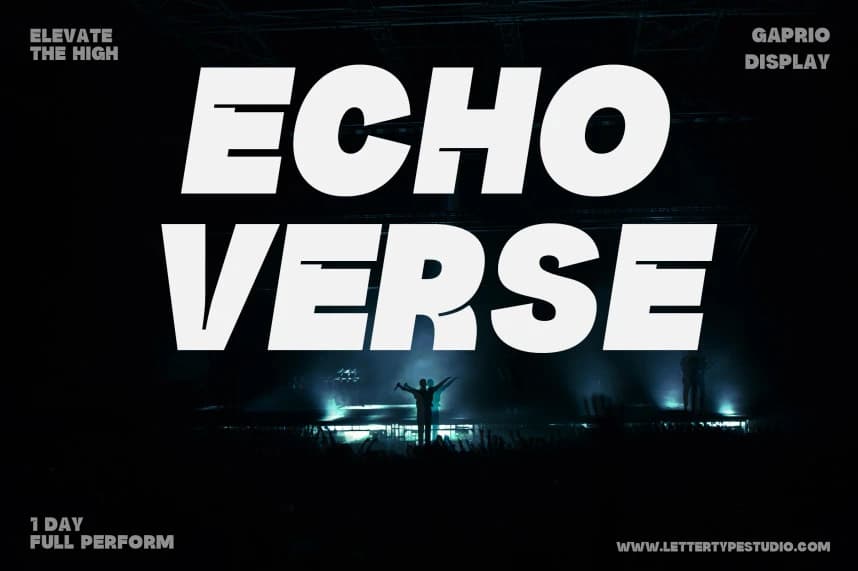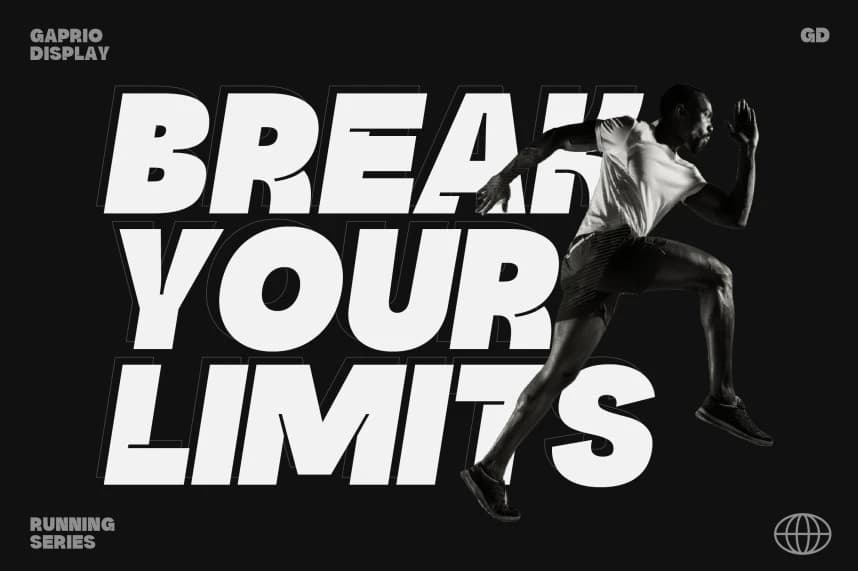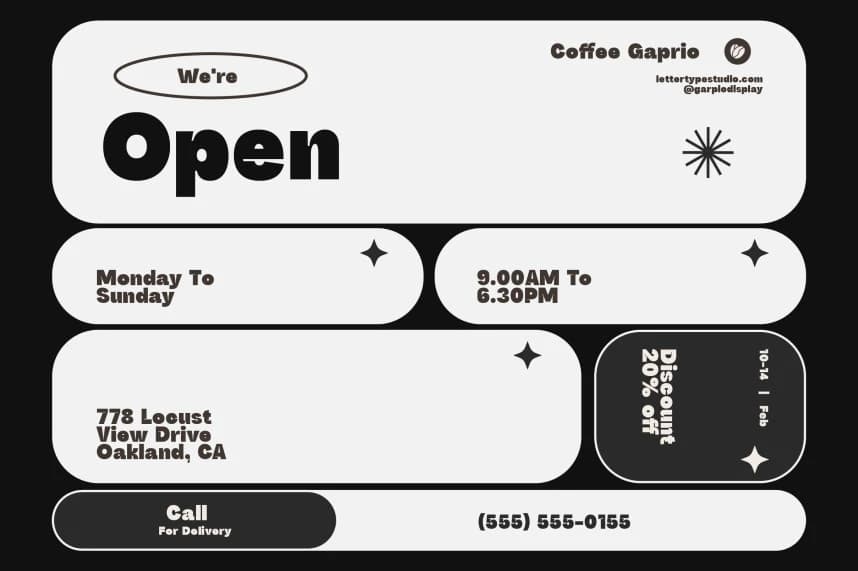
Gaprio Display Font
Gaprio Display Font, modern markalaşma, editoryal düzenler, afişler ve moda odaklı tipografi için tasarlanmış cesur geometrik bir display sans'tır. Güçlü oranlar, temiz eğriler ve kendinden emin görsel ritim ile tasarlanmıştır. Bu yazı tipi çağdaş minimalizm ile exp arasında çarpıcı bir denge sunar.
Gaprio Display Font, modern branding, editoryal düzenler, posterler ve moda odaklı tipografi için tasarlanmış cesur bir geometrik display sans'tır. Güçlü oranlar, temiz eğriler ve kendinden emin görsel ritimle tasarlanan bu yazı karakteri, çağdaş minimalizm ile ifade dolu gösterim estetiği arasında çarpıcı bir denge sunar.
Gaprio Display